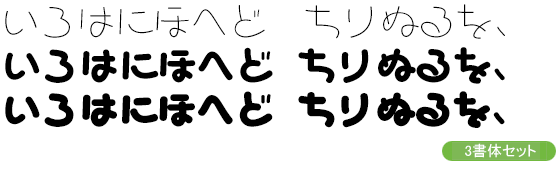
手書き風書体
ほんまるかなOTF-H
HommaruKana-H
かすかに筆文字の名残り、味わいのある丸もじ。やや左上に重心がある独特のフォルム。既存の他社丸ゴシックと組み合わせても違和感なく溶け込み、あたたかな雰囲気を醸し出します。
縦組み・横組みのすべての文字にペアカーニングをほどこしており、メトリクス処理をするだけで、バランスのとれた組みが得られます。お得な9ウェイトセットもあります。